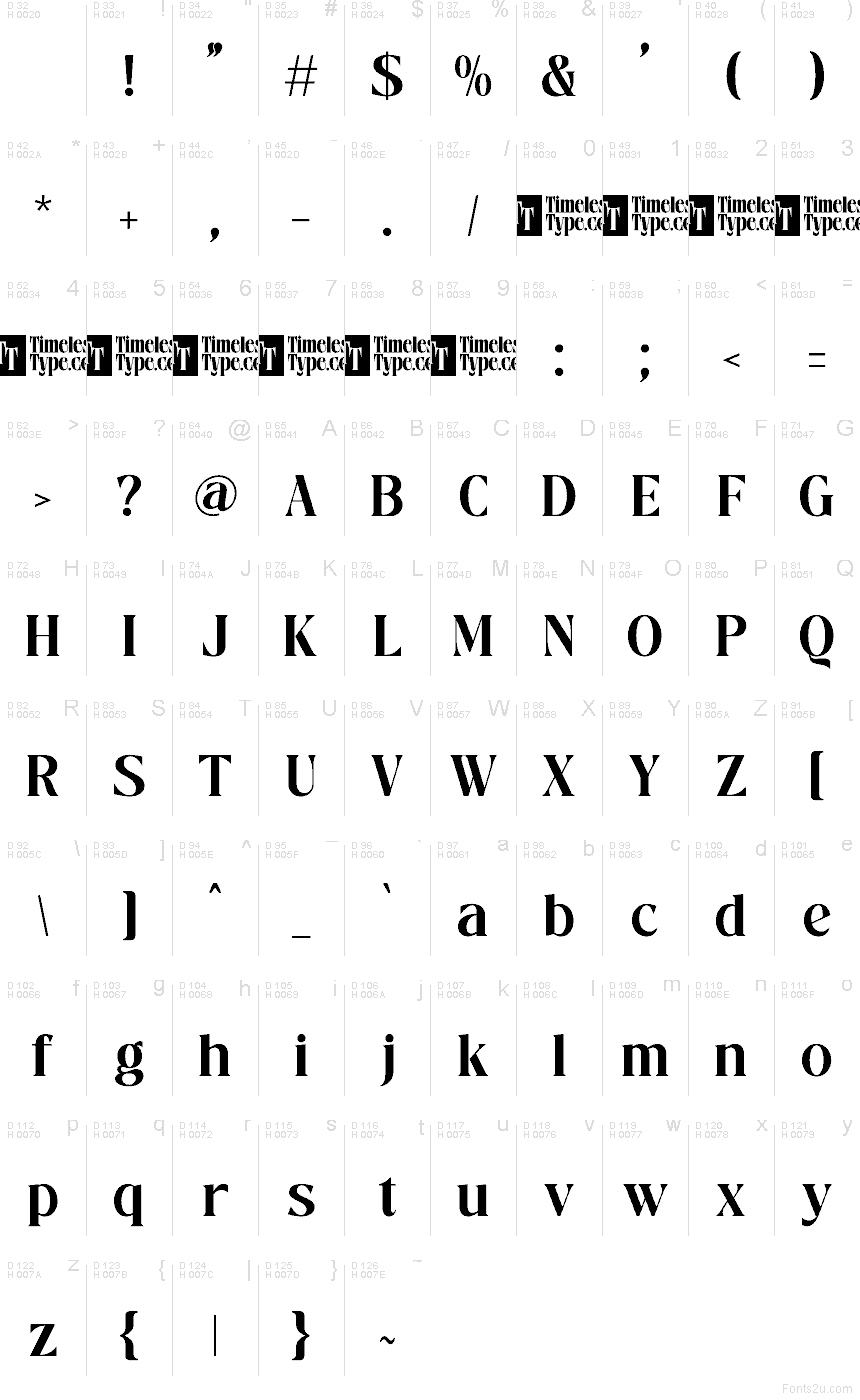
Mistical Spring da TimelessType.co é uma fonte serifada gratuita de alto contraste, com o impacto elegante dos cabeçalhos das revistas de moda. Suas letras alongadas combinam traços verticais largos com linhas ultrafinas e serifas longas e afiadas como navalhas. As proporções são imponentes, embora várias curvas terminem em cortes nítidos e surpreendentes.
Esse visual editorial de moda é perfeito para capas de revistas, embalagens de perfumes e branding de boutiques. Em cartazes de eventos, as maiúsculas imponentes podem compor um monograma ou emblema decorativo, indo além de uma simples tipografia de título.